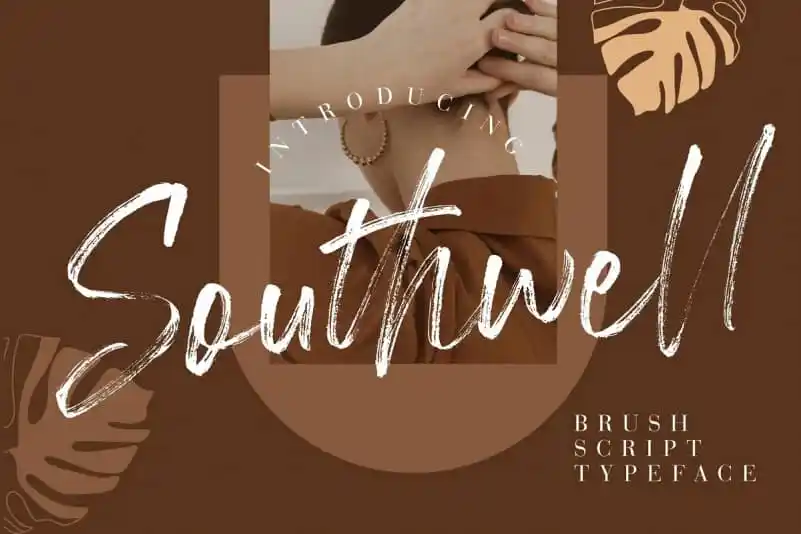
Southwell Brush Font – Download Grátis
A Southwell Brush Font é uma elegante escolha para quem busca adicionar um toque pessoal a suas criações digitais. Ela traz características de traçado delicado e mistura influências do hand lettering, resultando num efeito fresco e moderno que certamente daria ao seu design o toque personalizado desejado. Ideal para uso em identidades gráficas, headlines ou qualquer lugar onde desejar um ar artesanal, a Southwell Brush Font é uma fonte de letra script perfeita. Seja você designer, grafista ou criador de materiais digitais, essa fonte será definitivamente o item adicional que dará seu trabalho aquela pitada especial e única que fazem toda a diferença.